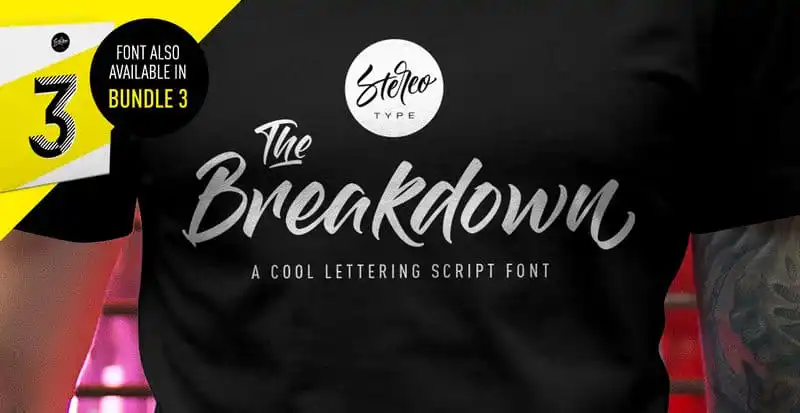
The Breakdown Script Font – Fonte Grátis
The Breakdown Script Font
Introduzimos The Breakdown Font! Desenvolvida e compartilhada pelo designer StereoType, essa fonte é a versão suave do Gloss & Bloom, originalmente desenhado por Sean Delloro. O estilo Fresh & moderno de The Breakdown é perfeito para criações como logomarcas, marcas de marca, cartões de aniversário, panfletos e qualquer projeto gráfico que você possa ter. Seja em um design sofisticado ou casual, The Breakdown tem o poder de dar uma sensação de frescura e atualidade a seu trabalho. Experimente essa fonte amigável e versátil para tornar seus projetos ainda mais impecáveis.